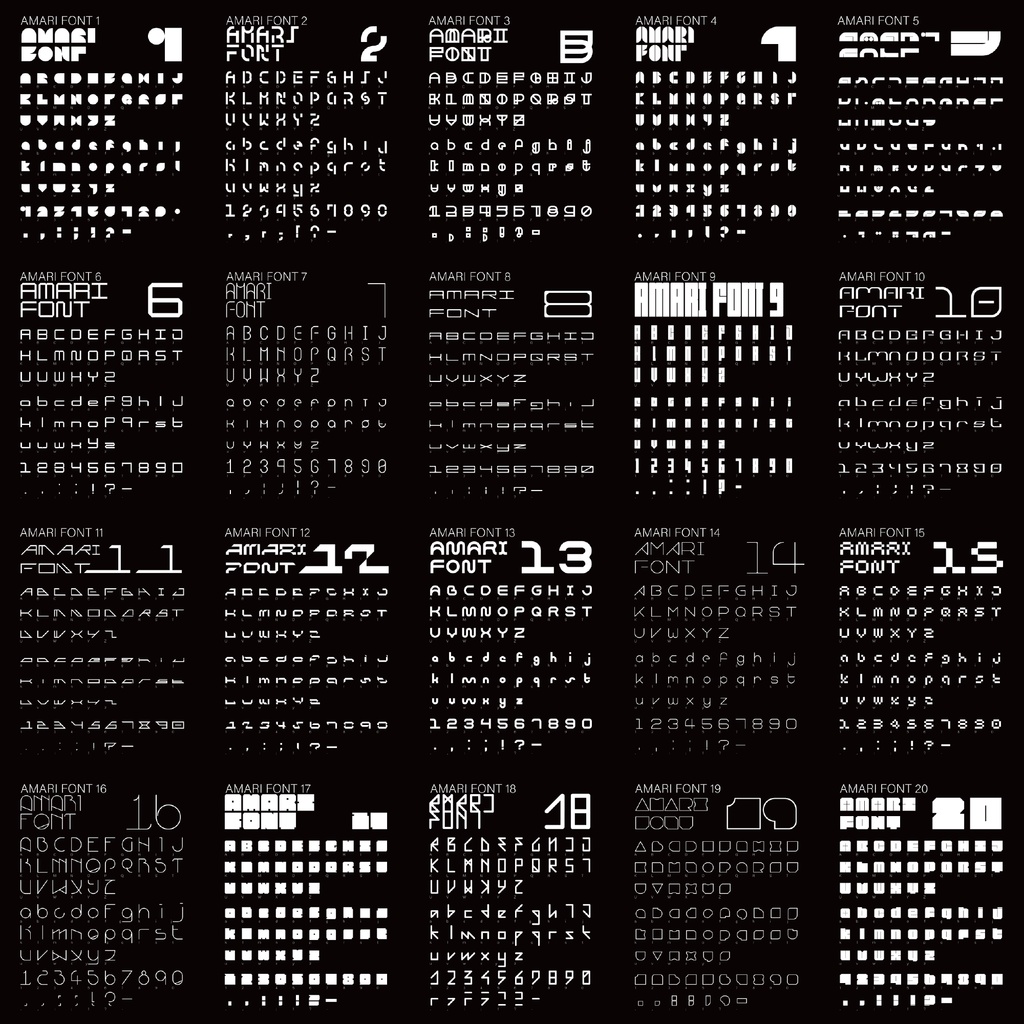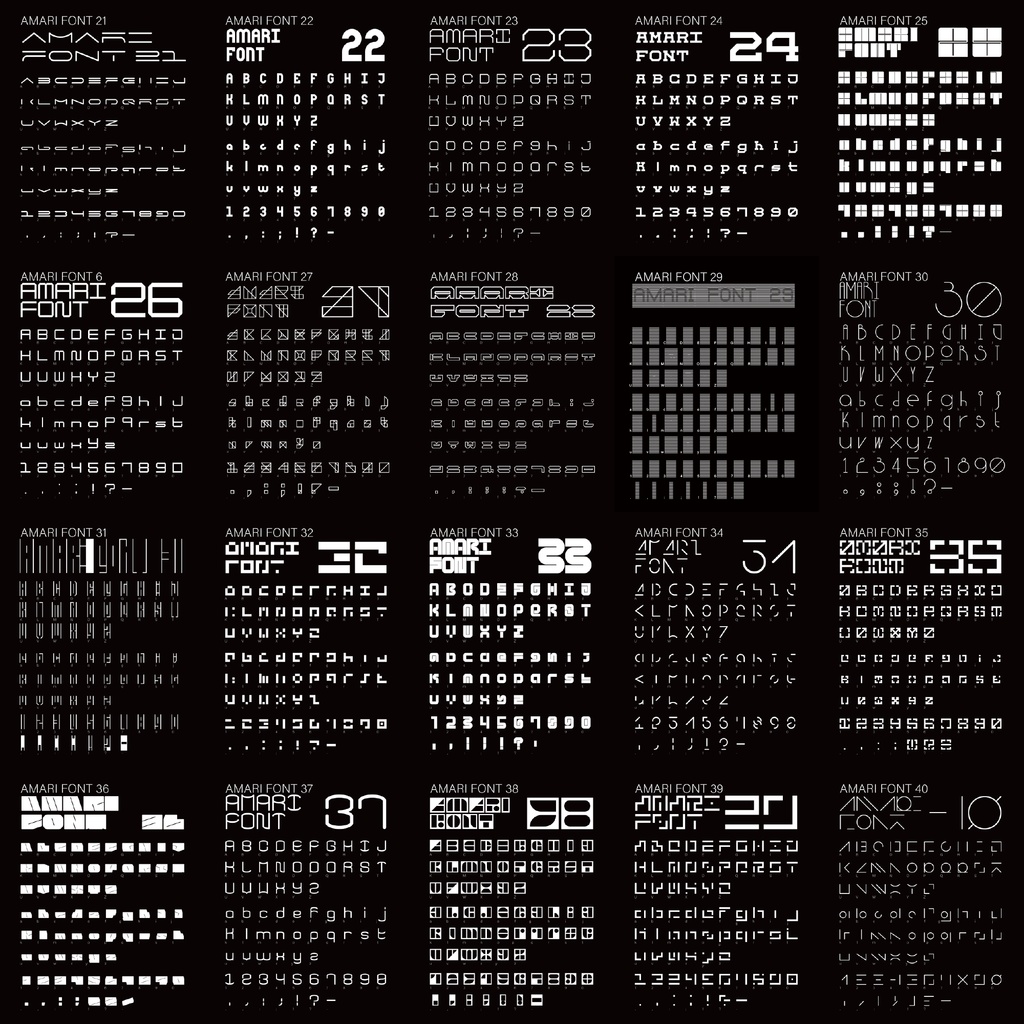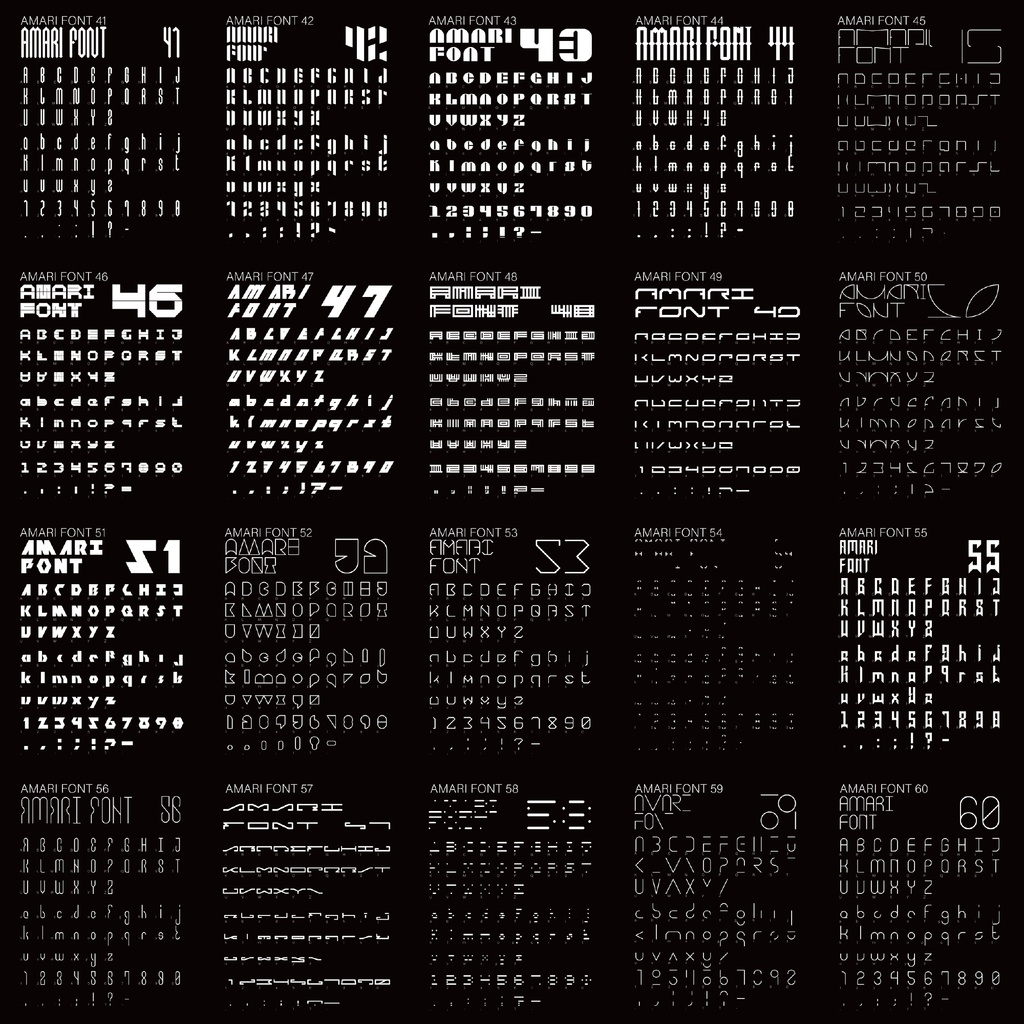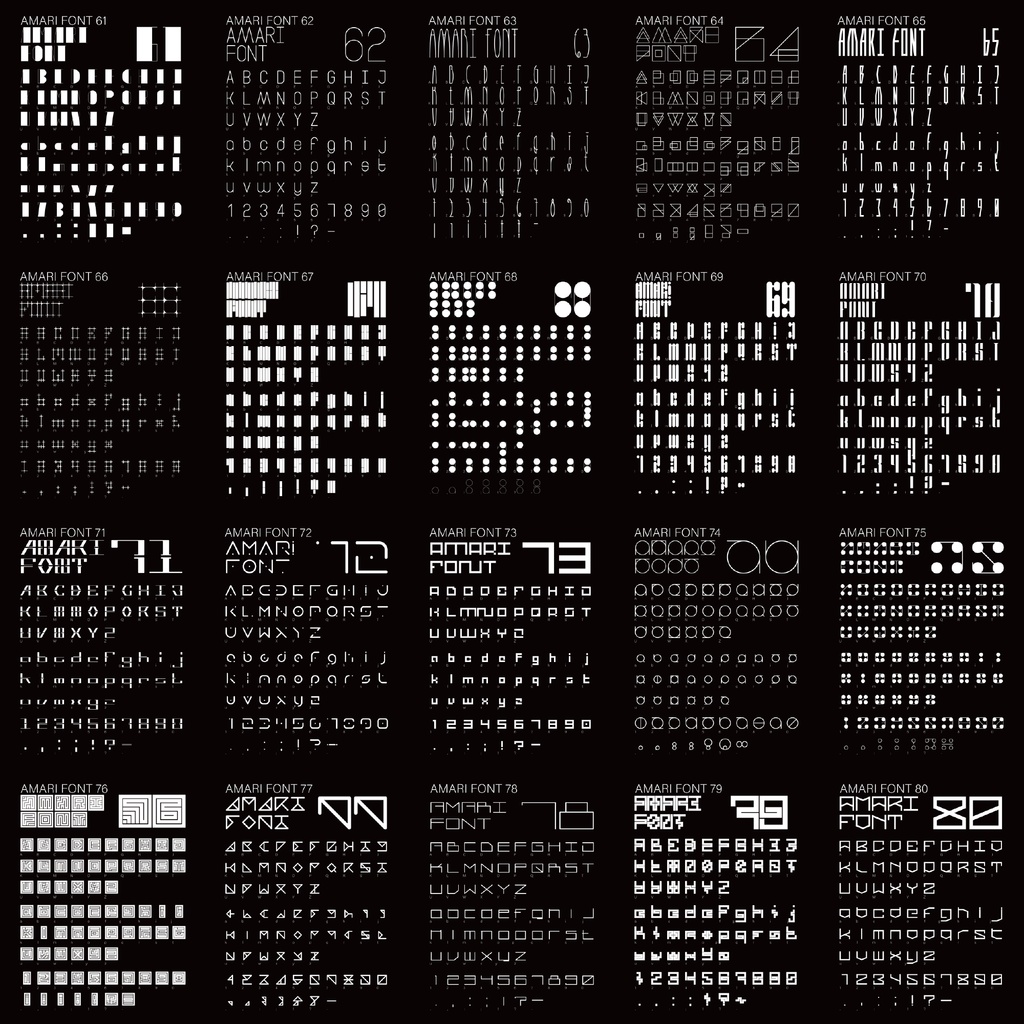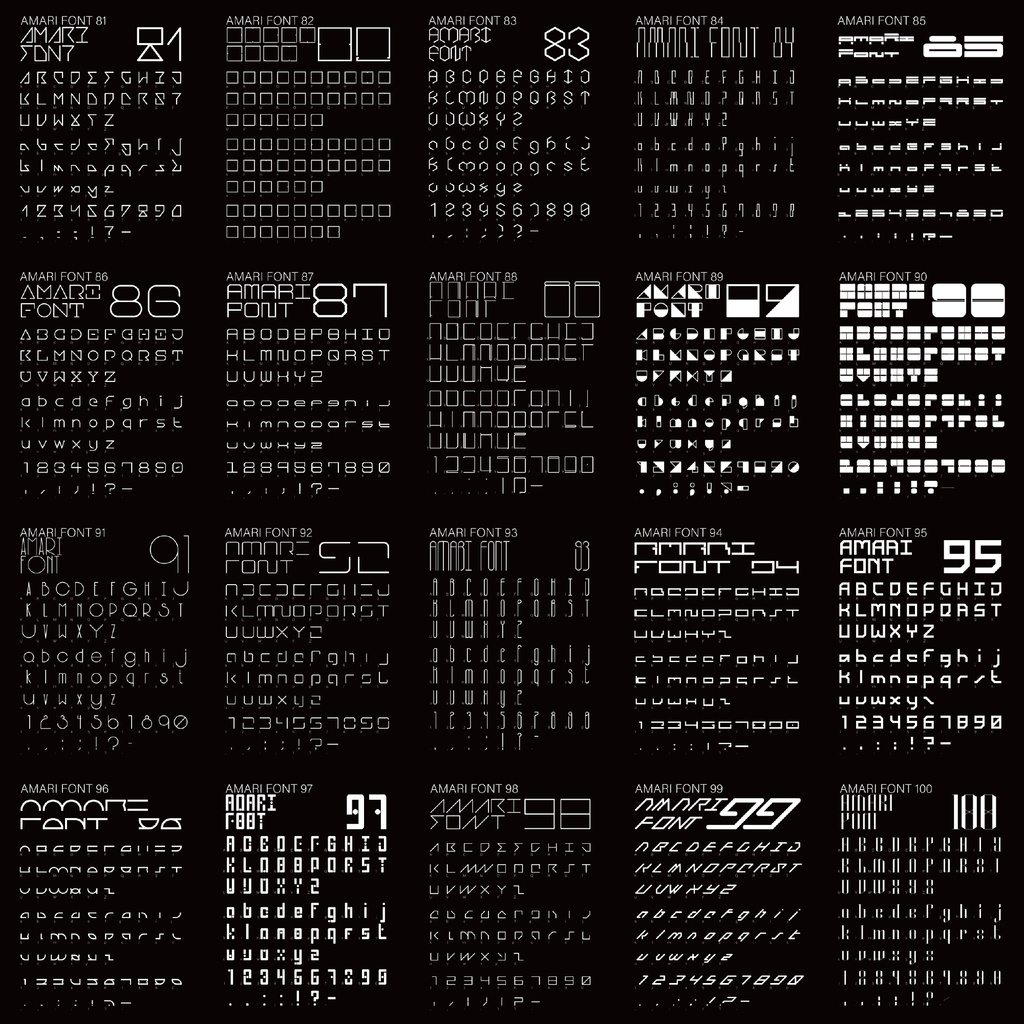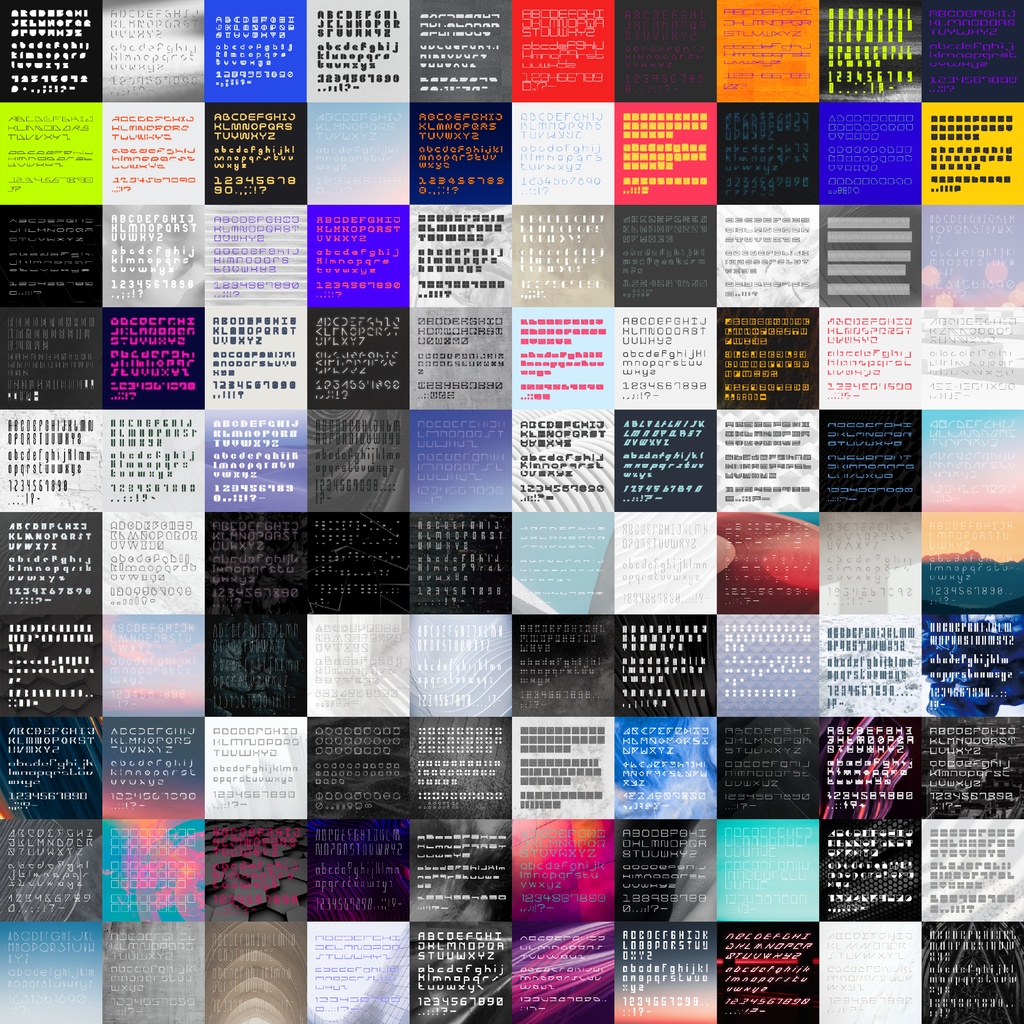
Amari #100日フォントチャレンジ 全作品の集合パック 📢📢📢特記事項📢📢📢 #100日フォントチャレンジ #100日チャレンジ 当初の目的は、効率を挑戦する、同じテーマの発想力。そして自身の作品を増やするのため。 100日を経て、ようやく100フォントが完成しました。この100フォントの中には良くないと思われるフォントもありますが、でも全体としては無事完走させることができました。 今回のチャレンジで一番感じたのは、時間のなさと自分の効率の悪さです。 ほとんどのフォントが、最初は多くの可能性を持っていたもの、時間が足りずに中断してしまった。 この後、時間のある時に少しずつ各フォントを更新していきますので、楽しみにしていてください。 📢📢📢デザイン説明📢📢📢 フォントのデザイン方法が多くは、スーパーミニマムフォント、ビジュアルバランス、メカニカル感、暗号化、幾何学的な組み合わせです。 時間的な制約のため、セリフフォントを1日で完成させるのは難しい。 まだ、手書き文字に自信がありません。 そのため、フォントはシンプルなものが多いですね。 そう、この表紙は完全にゆうたONEさんのデザインを真似たものです。 表紙の後には、各フォントの番号を識別しやすいように視覚的に調整された5枚の参考です。 📢📢📢利用規約📢📢📢 個人、商用どちらでも利用可能です。 ⚠️これらのフォントを使用する場合、必要に応じて微調整を行うことは可能ですが、フォントの構造を変更することはできません。また、可変フォントをデフォルトの範囲外の量に手動で調整することはできません。⚠️ もしもこのフォントが使用されたら、https://twitter.com/amari_designに教えていただけるとうれしいです! 本素材を使用した作品については、リツイートなどの形で宣伝させていただく場合があります。 フォントのインストール等の技術的なサポートはいたしません。使用して発生したと思われる如何なる問題についても、作者は責任を負わないものとします。 著作権を放棄することはありません。 商標を登録したり、作者であると主張したり、データ自体を販売または再販したりすることは禁じられています。 このコンテンツの最終的な解釈権は作者に帰属します。 ⚠️内容補充とバージョン更新は製作続けるです。使用する際は最新バージョンにご注意ください。⚠️ 📢収録內容 100フォント(一部は可変フォント) 大分のフォントはラテン文字、数字だけてを含む70文字が含まれています。 ーーーーーーーーーーーー Twitter:https://twitter.com/amari_design Behance:https://www.behance.net/9f45706b ーーーーーーーーーーーー